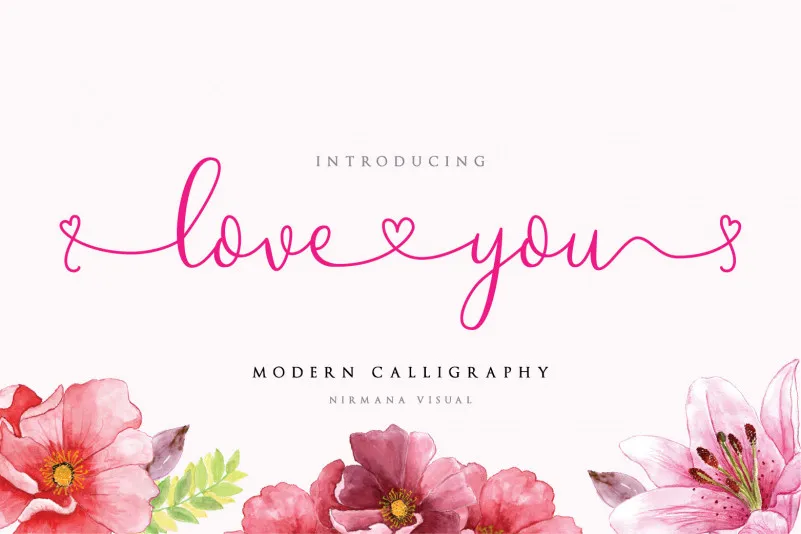
A fonte Loveyou – Romantic Font é uma moderna escolha para quem busca um toque romântico na sua marca ou design. Este exclusivo conjunto de caracteres é perfeito para criar identidades de marca, logotipos e convites de casamento, onde se precisa dar aquela pitada delicada de escrita a mão. Para quem procura uma fonte que combine modernidade com um toque nostálgico e encantador, Loveyou – Romantic Font é definitivamente o item certinho para seu design. Adaptável a diversas necessidades gráficas, ela permite dar um ar romântico a qualquer projeto sem comprometer a clareza do texto, tornando-se uma ótima opção para aqueles que buscam um toque especial em seus projetos. Seja você um designer de marca ou criador de conteúdo digital, Loveyou – Romantic Font é certamente o parceiro perfeito para adicionar aquela pitada de romantismo a qualquer projeto.